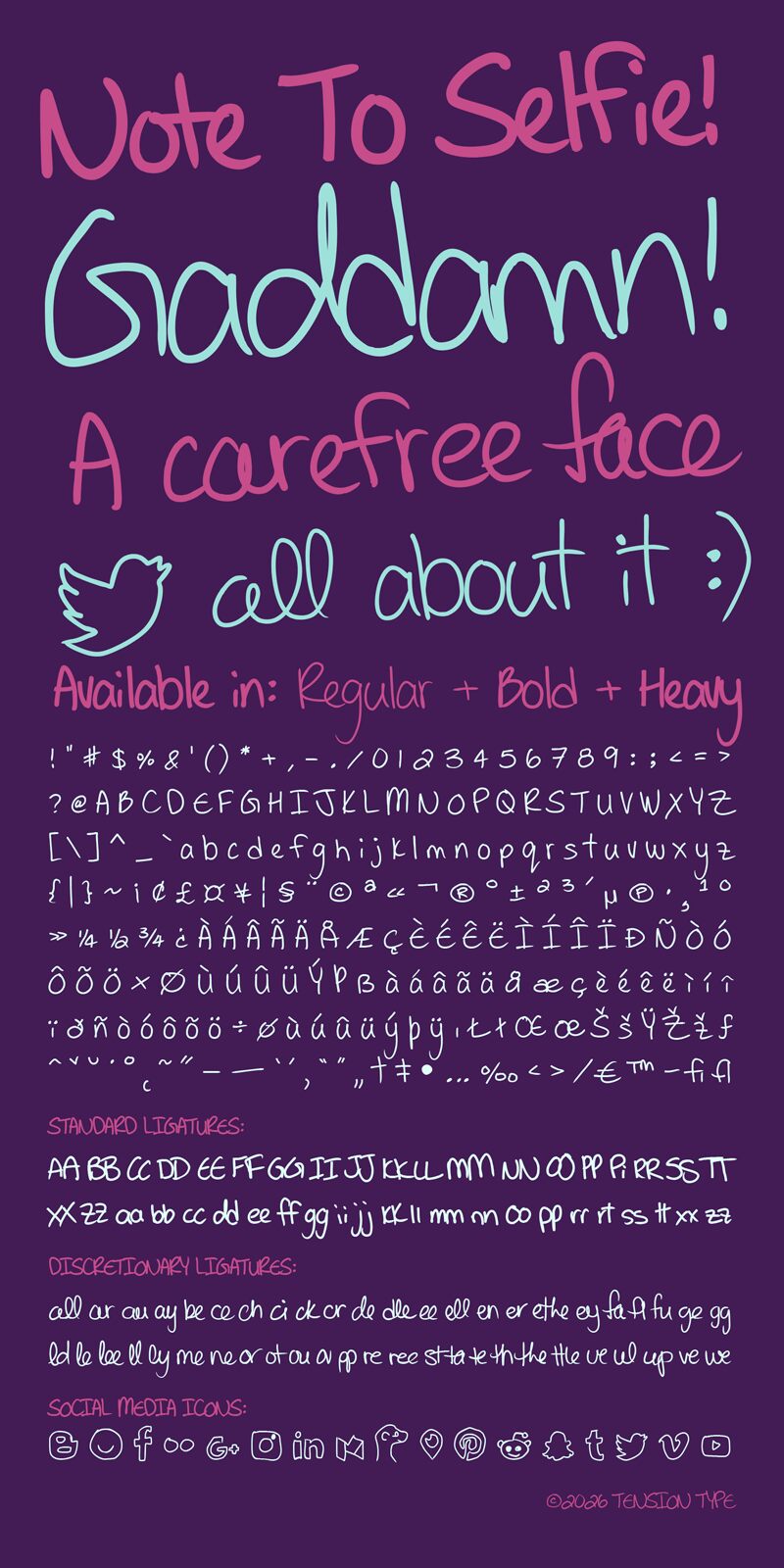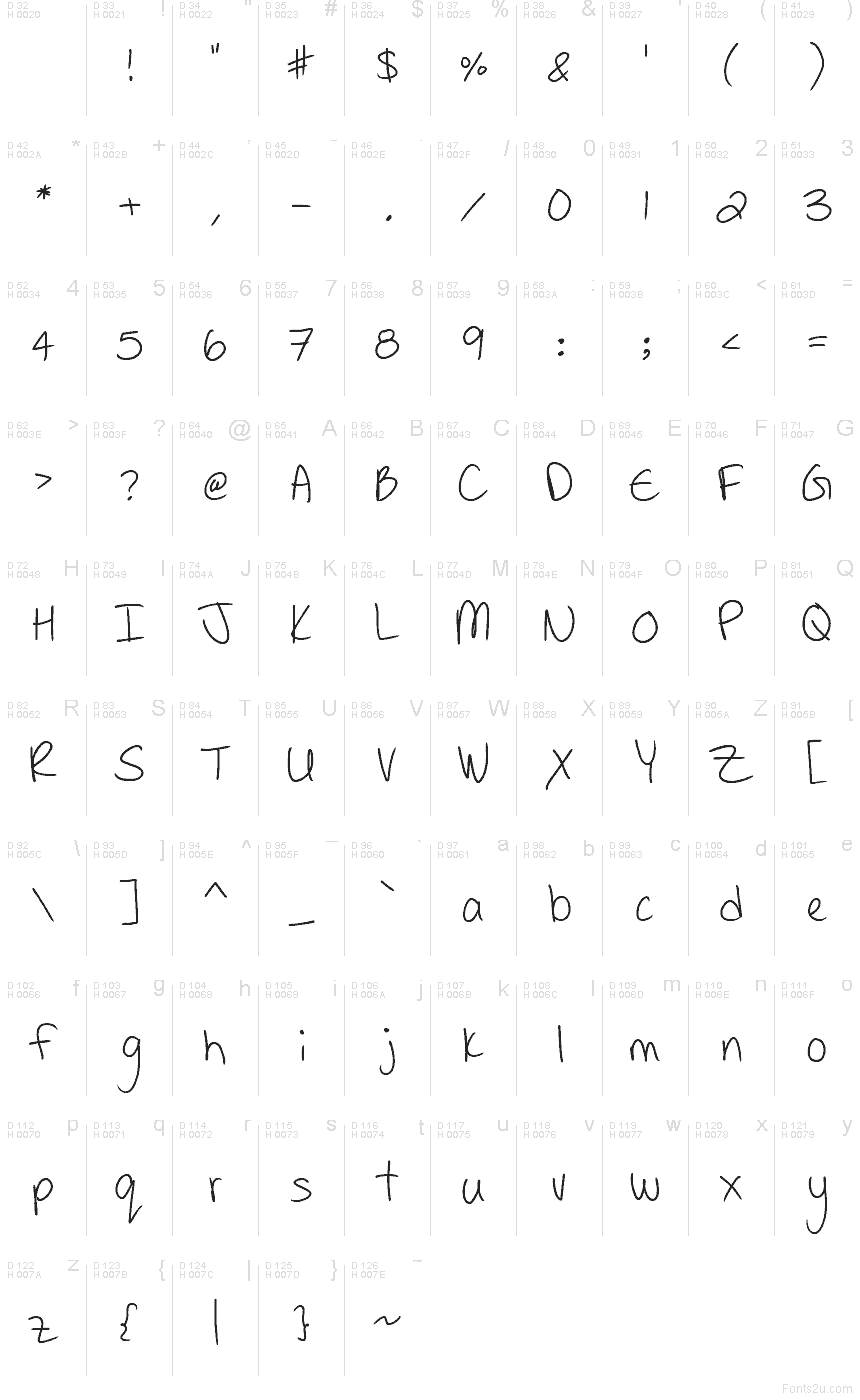
Note to Selfie di Tension Type è un font scritto a mano gratuito, caratterizzato da tratti rapidi e verticali che conferiscono alle lettere un ritmo simile a quello delle note a margine. Le forme sono semplici e leggermente irregolari, il che la rende più simile a un appunto personale che a una scrittura a pennello troppo levigata.
Ciò la rende una scelta naturale per grafiche di journaling, adesivi per planner, post informali sui social, titoli per scrapbooking ed etichette regalo. I titoli brevi e i testi in stile etichetta ne traggono il massimo vantaggio, poiché il ritmo stretto e calligrafico mantiene un tono informale pur dando a ogni parola una presenza ben definita.
Un altro carattere scritto a mano tra cui scegliere. Potrebbe sembrare un po' disordinato, ma ha un aspetto vero. Non è una famiglia nata da una rapida tracciatura automatica. Ci ho dedicato del tempo. Spero che sia adatta al tuo progetto.